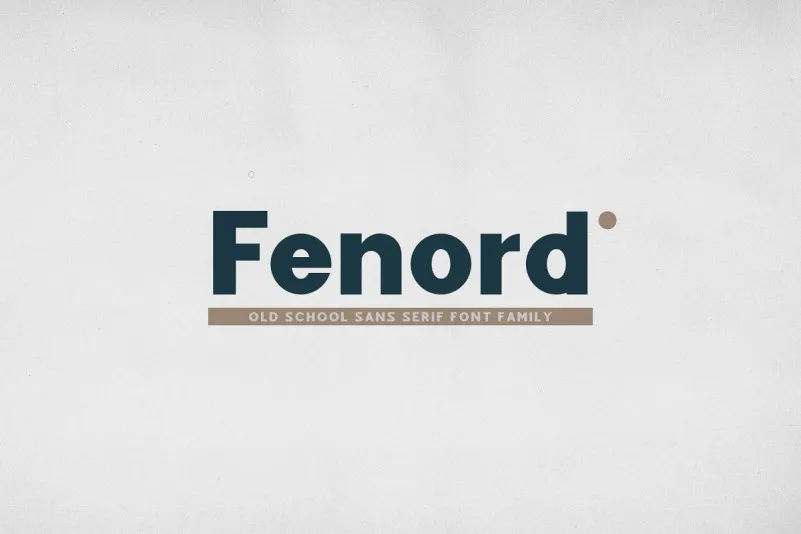
Fenord Sans Serif Font – Fonte Grátis
Fenord Sans Serif Font
Introduzimos a família de fontes serifadas sem sersemifontes “Fenord Font” – uma dupla de fontes serifadas sem sersemifontes criada pelo Craft Supply Co. Fenord Sans Serif Font foi inspirada nos livros de tipo especiais europeus, especialmente o padrão de tipo Fenord. Trazendo algumas vibrações gloriosas dos valores sólidos dos pioneiros e mantendo um olho no que as demandas atuais e tecnologia exigem, a fonte é perfeita para uso profissional altamente especializado. Com sua tipografia limpa e moderna, Fenord Sans Serif Font certamente adicionará um toque de sofisticação à qualquer projeto gráfico. Seja você designer, editor ou empresário, se quiser uma fonte sem sersemifontes que atende a todos os requisitos do seu trabalho, então “Fenord Font” é definitivamente para você.